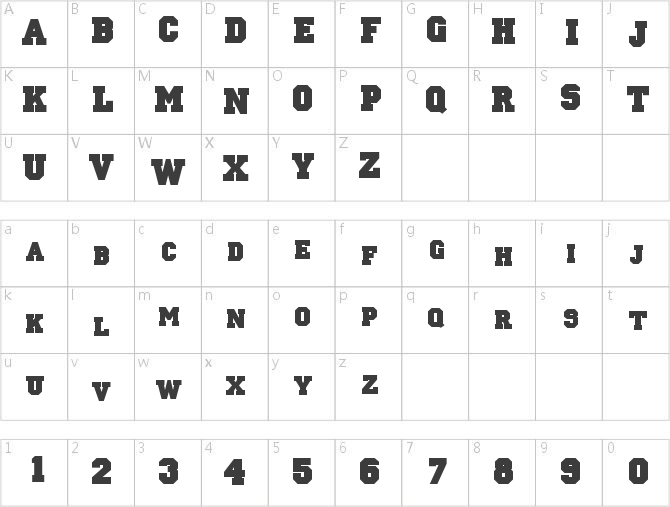
Letterman-Solid 詳情頁(yè)
Letterman-Solid字體字庫(kù)是一款讓人賞心悅目、百看不厭的英文字體,適合各類廣告和產(chǎn)品包裝設(shè)計(jì)應(yīng)用,字體大小0.04MB,格式為ttf字體,上傳用戶是Elieen,作者/版權(quán)方為未知